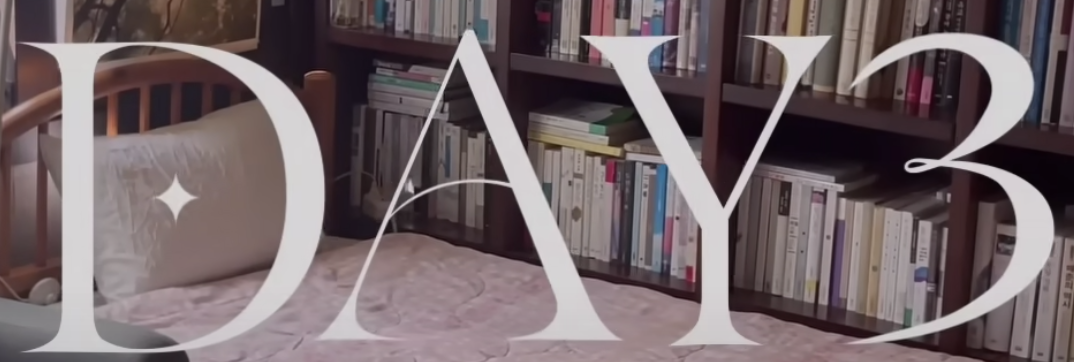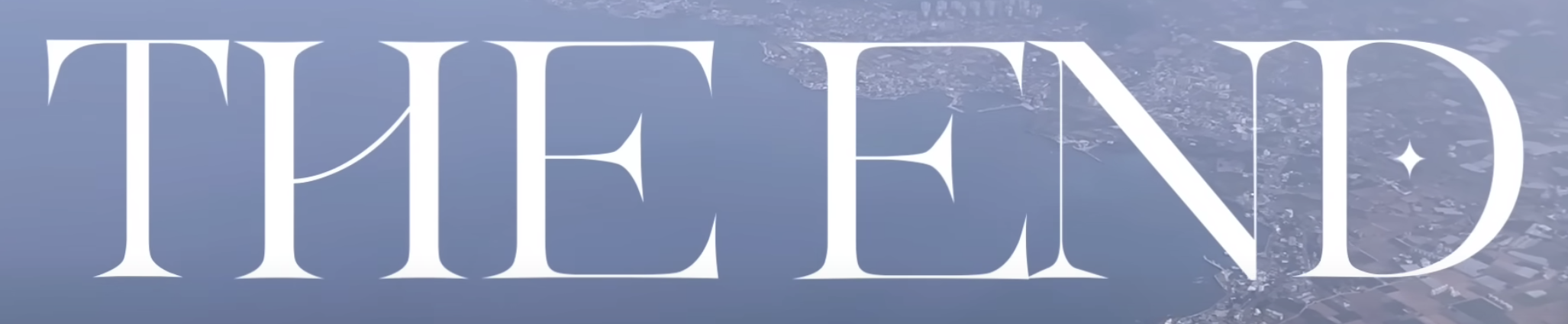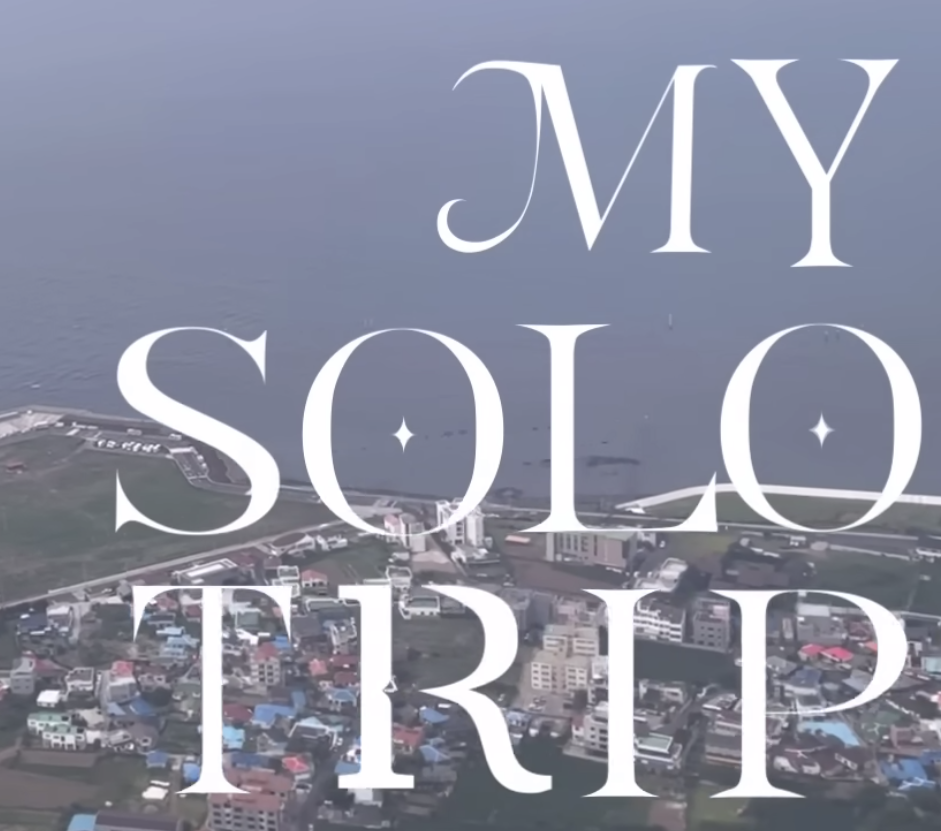
유튜브보다가 넘 궁금해서 문의드려요ㅜㅜ ele*** 2023.02.22 엄청 특이해 보이는데 어떤 폰트인지 검색해도 안나오네요 ㅠㅠ 혹시 아시는 분 계신가요? 댓글 0 등록 eua*** 저도 궁금해요 ㅋㅋㅋ큐ㅠㅠㅠㅠ 능력자분 없으신가요ㅠ 2023-03-06 답글 달기 115*** 저도 궁금한데 안나오네요 ㅠㅠ 2023-03-04 답글 달기 댓글 더보기 쉽고 빠르게 가장 비슷한 폰트를 알고 싶다면? 이미지로 검색하기
저도 궁금해요 ㅋㅋㅋ큐ㅠㅠㅠㅠ 능력자분 없으신가요ㅠ
저도 궁금한데 안나오네요 ㅠㅠ